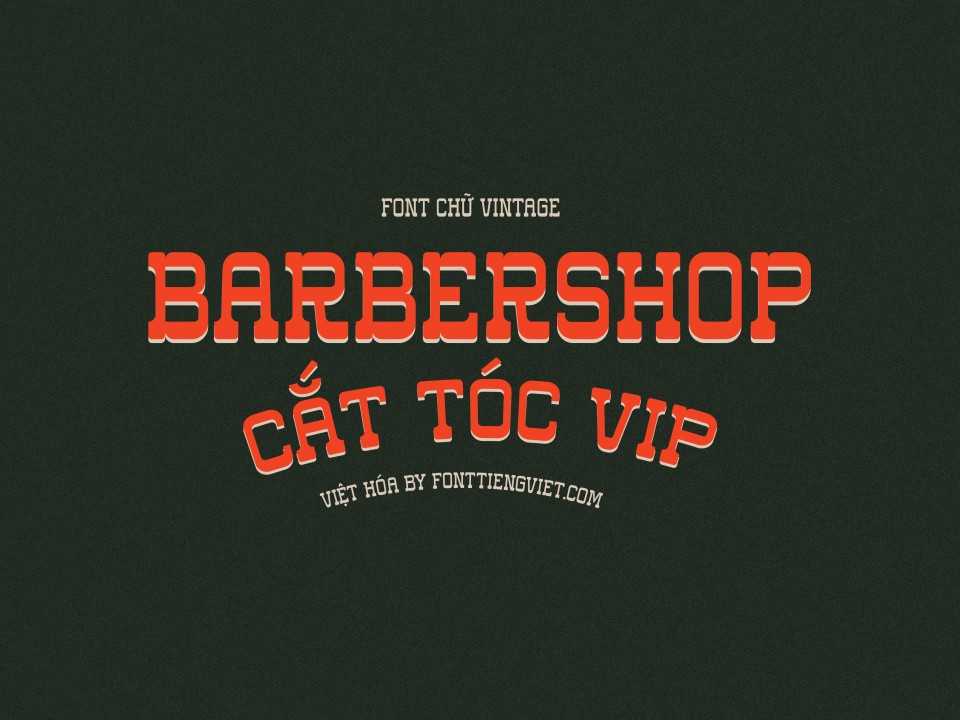
Font việt hóa 1FTV Vestern Carlo kiểu vintage retro
Giới thiệu về Font việt hóa 1FTV Vestern Carlo kiểu vintage retro
Trong thế giới đồ họa hiện đại, việc tìm kiếm một bộ Font Miễn Phí có phong cách hoài cổ luôn là ưu tiên hàng đầu của các nhà thiết kế. Font việt hóa 1FTV Vestern Carlo kiểu vintage retro là một lựa chọn hoàn hảo, mang đến vẻ đẹp đậm chất cổ điển của những thập niên trước. Với đường nét mạnh mẽ nhưng không kém phần uyển chuyển, bộ font này giúp truyền tải thông điệp một cách ấn tượng và có chiều sâu văn hóa.
Đặc điểm nổi bật của phông chữ
Bộ font này nổi bật với cấu trúc các chữ cái được chăm chút tỉ mỉ, mô phỏng hoàn hảo phong cách bảng hiệu quảng cáo xưa. Các nét thanh và nét đậm được kết hợp hài hòa, tạo nên sự cân bằng thị giác tuyệt vời. Đặc biệt, phiên bản 1FTV đã được tối ưu hóa đầy đủ dấu tiếng Việt, giúp người dùng dễ dàng ứng dụng vào các dự án thiết kế mà không lo lỗi hiển thị hay mất nét.
Ứng dụng thực tế của Font việt hóa 1FTV Vestern Carlo kiểu vintage retro
Thiết kế thương hiệu và ấn phẩm quảng cáo
Nhờ vẻ ngoài độc lạ, 1FTV Vestern Carlo thường xuyên được sử dụng cho tiêu đề tạp chí, bìa sách hoặc menu quán cà phê phong cách retro. Khả năng gây chú ý mạnh mẽ giúp bộ font này trở thành điểm nhấn quan trọng trên các poster sự kiện hay bao bì sản phẩm truyền thống. Sự linh hoạt trong cách thể hiện giúp nó phù hợp với cả môi trường giáo dục và sáng tạo nghệ thuật.
Lưu ý khi sử dụng trong đồ họa
Để đạt hiệu quả thẩm mỹ cao nhất, bạn nên kết hợp font chữ này với các tông màu trầm như nâu đất, vàng mỡ gà hoặc xanh rêu. Việc điều chỉnh khoảng cách chữ (kerning) hợp lý cũng giúp đoạn văn bản trở nên thanh thoát và dễ đọc hơn trên nhiều thiết bị khác nhau.